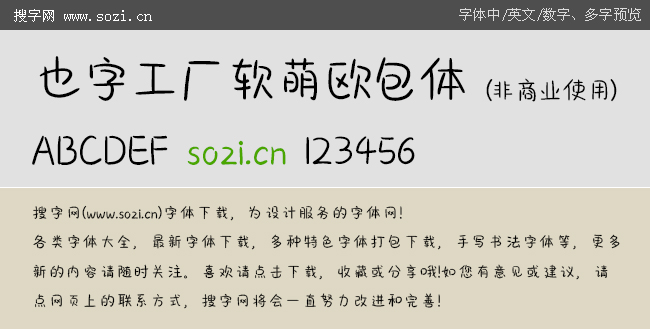
也字工厂软萌欧包体
搜字网给大家提供一款也字工厂软萌欧包体(非商业使用)中文字体下载,也字工厂软萌欧包体是一款略带卡通风格的手写字体,字体书写自然流畅,又带有一点趣味性,具有很好的视觉效果。适合应用于儿童绘本、儿童海报、网页设计等应用(此字体为个人非商用版,商用可以联系:官方网址:https://yefont.com/home,联系方式:13798980448)。